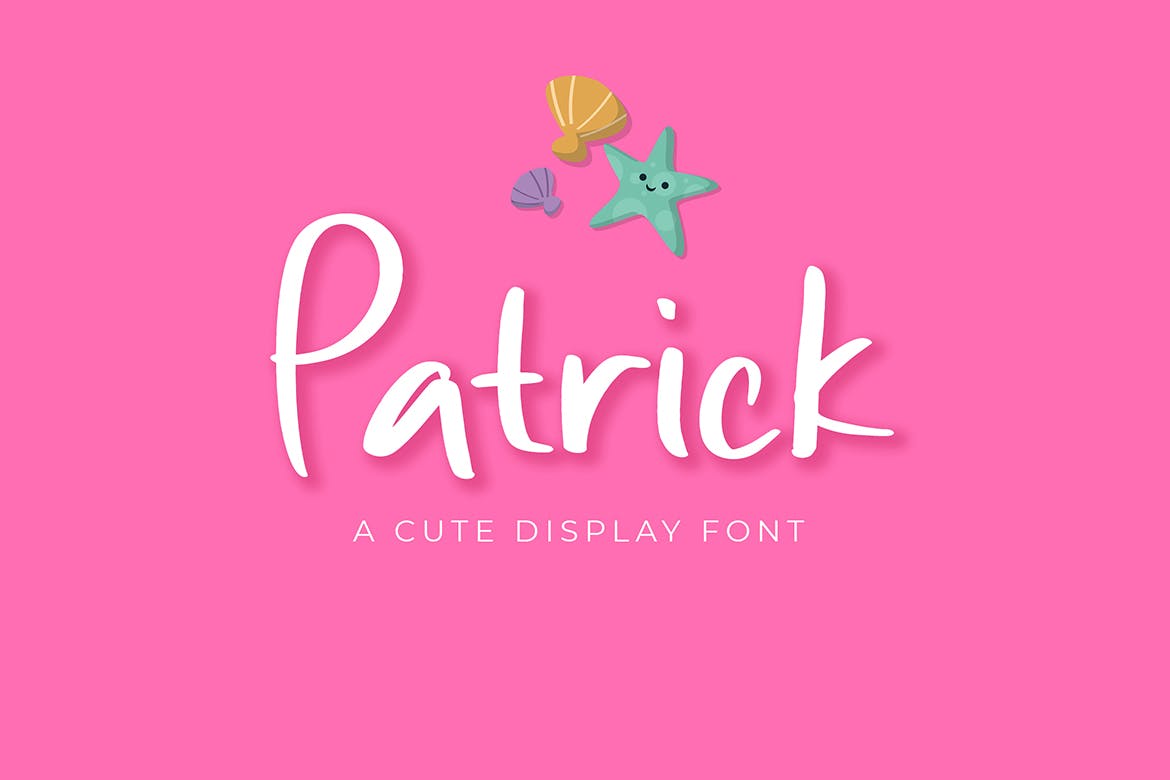
Patrick Cute Display Font
Patrick Cute Display Police
Patrick Cute Display Police est une police d'affichage mignonne et étonnante qui fera ressortir les motifs sur le thème des enfants !
Patrick est parfait pour les projets de marque, le logo, la conception de couvertures de livres, les conceptions de t-shirts, les publications sur les réseaux sociaux, les publicités, les emballages de produits, les conceptions de produits, les étiquettes, les filigranes, les invitations, les articles de papeterie et tous les projets.